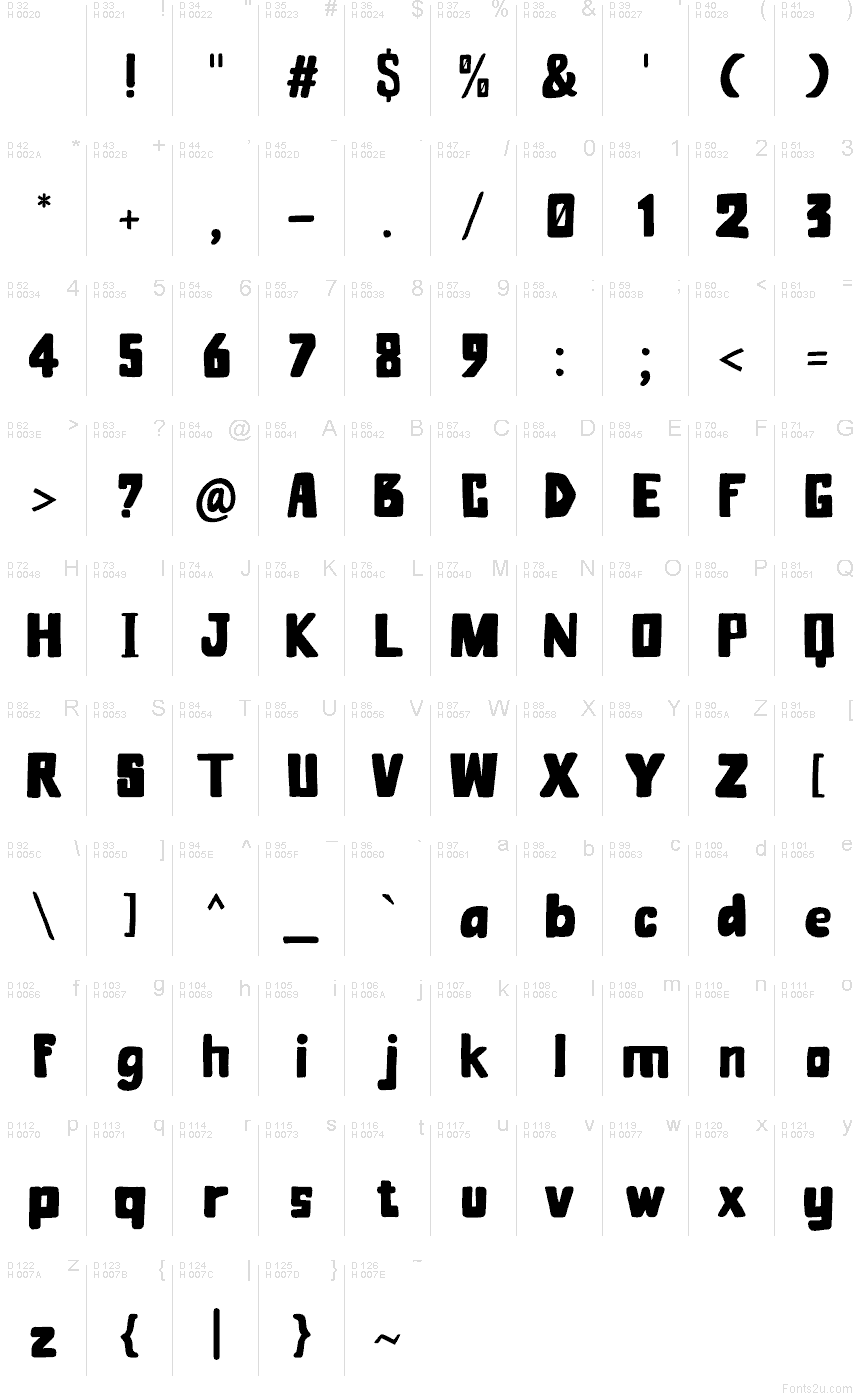
Blok Blokan od Hello Good Studio je bezplatný, masivní retro display font s hravým, ručně vyřezávaným dojmem. Písmena vypadají jako vytesaná z měkkých bloků, mají zaoblené rohy, zúžené proporce a drobné úhlové zářezy, které dodávají těmto těžkým tvarům živost.
Hodí se přirozeně do titulků na plakátech, obalů na snacky či street food, obálek dětských knih, skic log a výrazné grafiky na sociální sítě, kde tento bezplatný font utáhne krátkou frázi už jen svou osobností. Použijte ho pro titulní karty, krátký branding nebo nadrozměrné iniciály, když chcete, aby jeho kompaktní, přátelská váha a ty svérázné vyřezávané detaily odvedly svou práci.